Explorando las curvas y líneas en tipografía serif
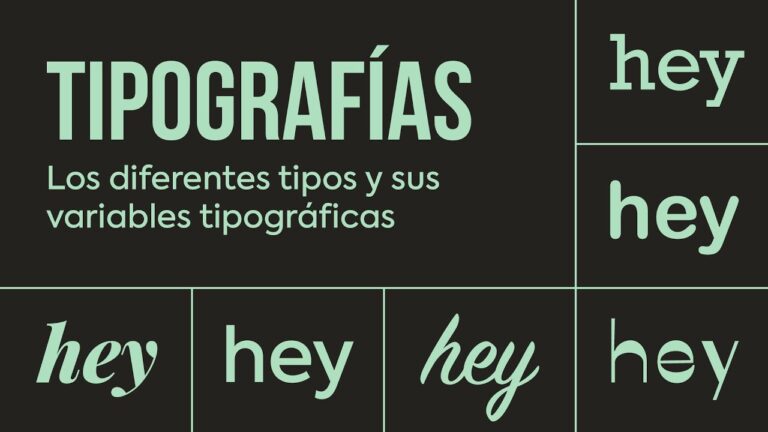
Las curvas y líneas en la tipografía serif son elementos clave que aportan elegancia y sofisticación a cualquier diseño. En este artículo, exploraremos la importancia de estas características en la creación de textos impactantes y memorables. Descubre cómo jugar con las curvas y líneas en la tipografía serif puede elevar la estética de tus proyectos de diseño gráfico. ¡No te lo pierdas!
¿Qué significan las tipografías curvas?
Las tipografías curvas, también conocidas como tipografías caligráficas, suelen tener una tendencia a curvarse y a ligarse entre sí, lo que las hace fácilmente reconocibles. Estas fuentes suelen presentar curvas muy pronunciadas, lo que las hace ideales para representar conceptos como la fantasía, la creatividad, la elegancia o la empatía, según la psicología tipográfica.
El diseño de estas fuentes aporta un toque de elegancia y creatividad a cualquier texto o diseño en el que se utilicen. Las curvas pronunciadas de las tipografías caligráficas les confieren un aspecto fluido y dinámico, lo que las hace ideales para transmitir emociones y sensaciones a través del texto.
En resumen, las tipografías curvas, como las caligráficas, tienen la capacidad de representar conceptos como la fantasía, la creatividad, la elegancia y la empatía. Su diseño fluido y dinámico aporta un toque de elegancia y creatividad a cualquier texto o diseño en el que se utilicen, lo que las hace una elección popular en el ámbito del diseño gráfico y la tipografía.
¿Qué transmite una tipografía con serif?
Todas las fuentes Serif tienen en común que simbolizan y transmiten autoridad, confianza, dignidad y firmeza. Se caracteriza por su estilo elegante y a la vez tradicional. Estas fuentes tienen sus inicios en la época en la que se tallaban bloques de piedra. Las serifas en las letras ayudan a guiar la mirada de manera fluida a lo largo del texto, haciendo que la lectura sea más cómoda y agradable. En resumen, una tipografía con serif es ideal para transmitir seriedad y profesionalismo en cualquier proyecto de diseño gráfico o editorial.
¿Cuál es el nombre de la tipografía de líneas?
La tipografía de líneas se conoce como tipografía serif, y se caracteriza por las líneas unidas a las letras. Su origen es incierto, aunque una teoría sugiere que los escribas dejaban pequeñas marcas al terminar cada trazo al usar pinceles o plumas.
Descubriendo la elegancia de las tipografías serif
Las tipografías serif son sinónimo de elegancia y sofisticación en el mundo del diseño. Con sus pequeños remates y detalles ornamentales, estas fuentes aportan un toque de distinción a cualquier proyecto. Ya sea para un logotipo, un cartel o un libro, las serifas son la elección perfecta para transmitir una imagen clásica y refinada.
Al utilizar tipografías serif, se logra dar a los textos una apariencia más formal y profesional. La estructura y legibilidad que ofrecen estas fuentes hacen que el contenido se vea más organizado y fácil de leer. Además, su estilo atemporal las convierte en una opción versátil que se adapta a una amplia gama de diseños y estilos. ¡Descubre la elegancia de las serifas y dale a tus creaciones un toque de distinción!
Explorando la belleza de las líneas y curvas en la tipografía serif
Las líneas y curvas en la tipografía serif son elementos esenciales que realzan la belleza y elegancia de cualquier diseño. La forma en que estas líneas se entrelazan y las curvas suaves se complementan entre sí, creando una armonía visual que atrae la mirada y transmite sofisticación. Explorar la creatividad que ofrecen las líneas y curvas en la tipografía serif es una oportunidad para crear diseños impactantes y memorables que cautivan a cualquier espectador.
En resumen, las curvas y líneas en tipografía serif añaden elegancia y sofisticación a cualquier diseño. Su versatilidad permite crear piezas visuales impactantes y profesionales. No subestimes el poder de estas formas en la comunicación visual, ya que pueden marcar la diferencia entre un diseño común y uno excepcional. Experimenta con las curvas y líneas en tus proyectos y observa cómo elevan la estética y la legibilidad de tus composiciones tipográficas. ¡Deja que la belleza de las serifas te inspire a crear diseños memorables y únicos!